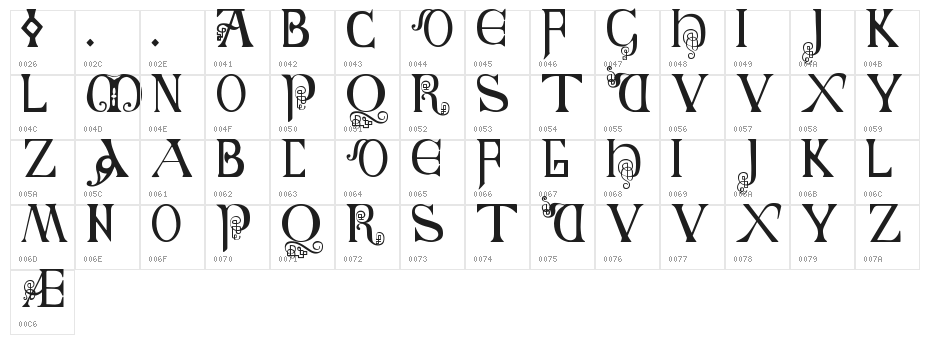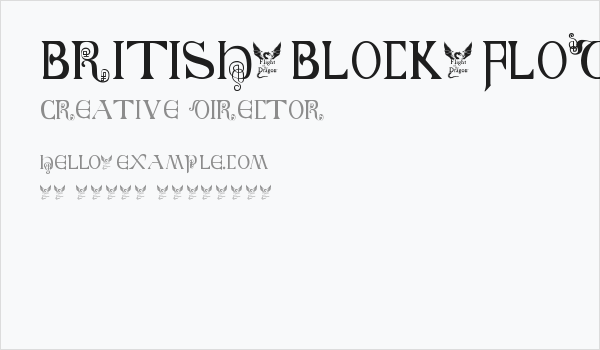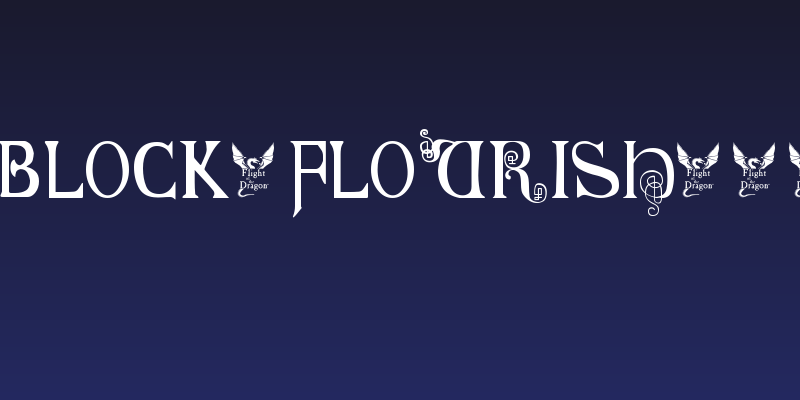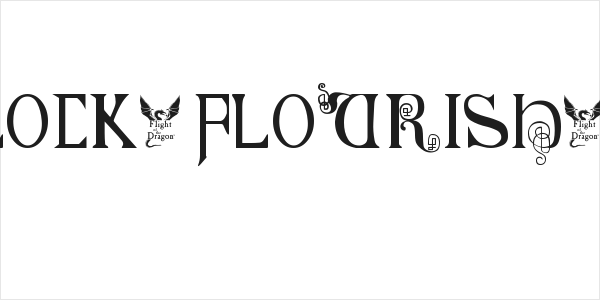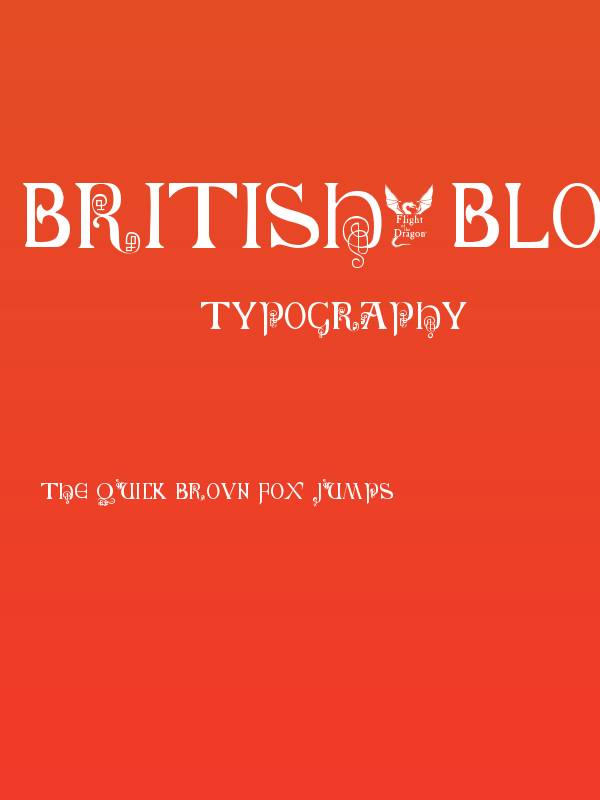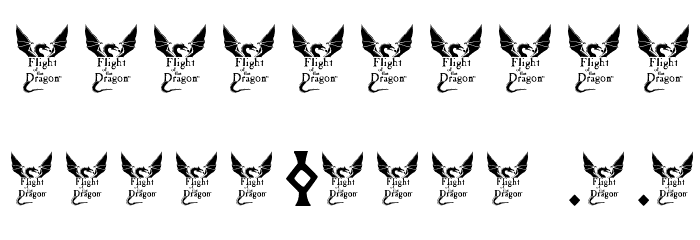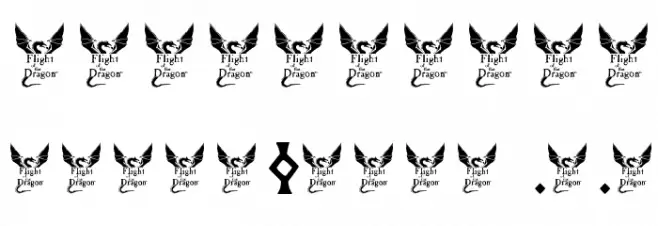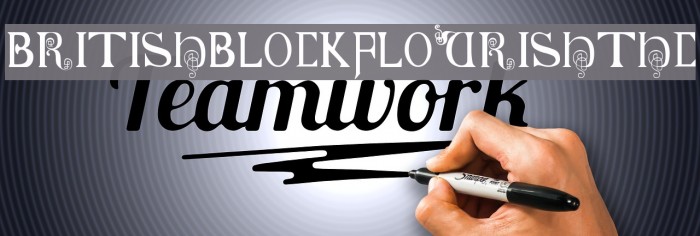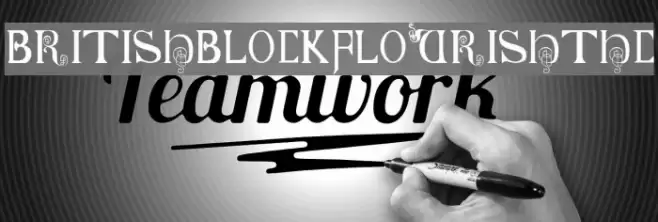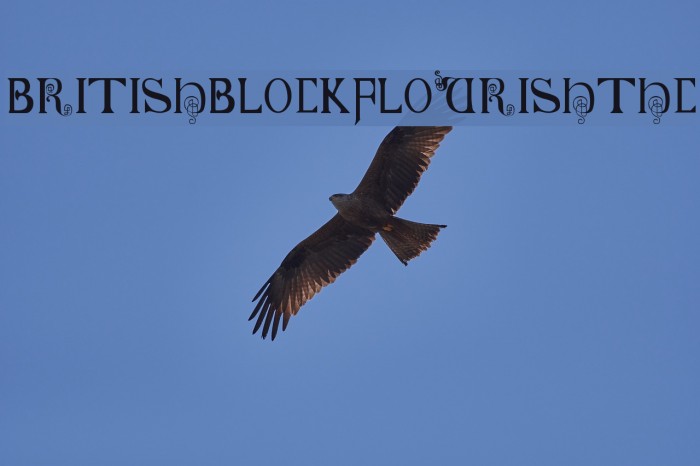
British-Block-Flourish--10th-c- Font
BRITISH-BLOCK-FLOURISH-10TH-C Litere mari
BRITISH-BLOCK-FLOURISH-10TH-C Litere mici
BRITISH-BLOCK-FLOURISH-10TH-C Alte caractere
| Proiecte propuse | Perfect for invitations, event programs, book covers, or any project requiring a historical or fantasy aesthetic. |